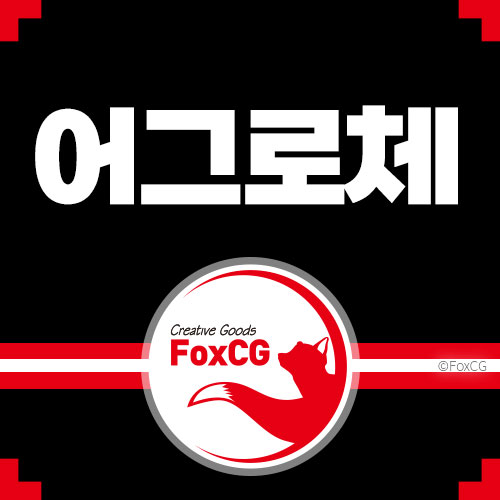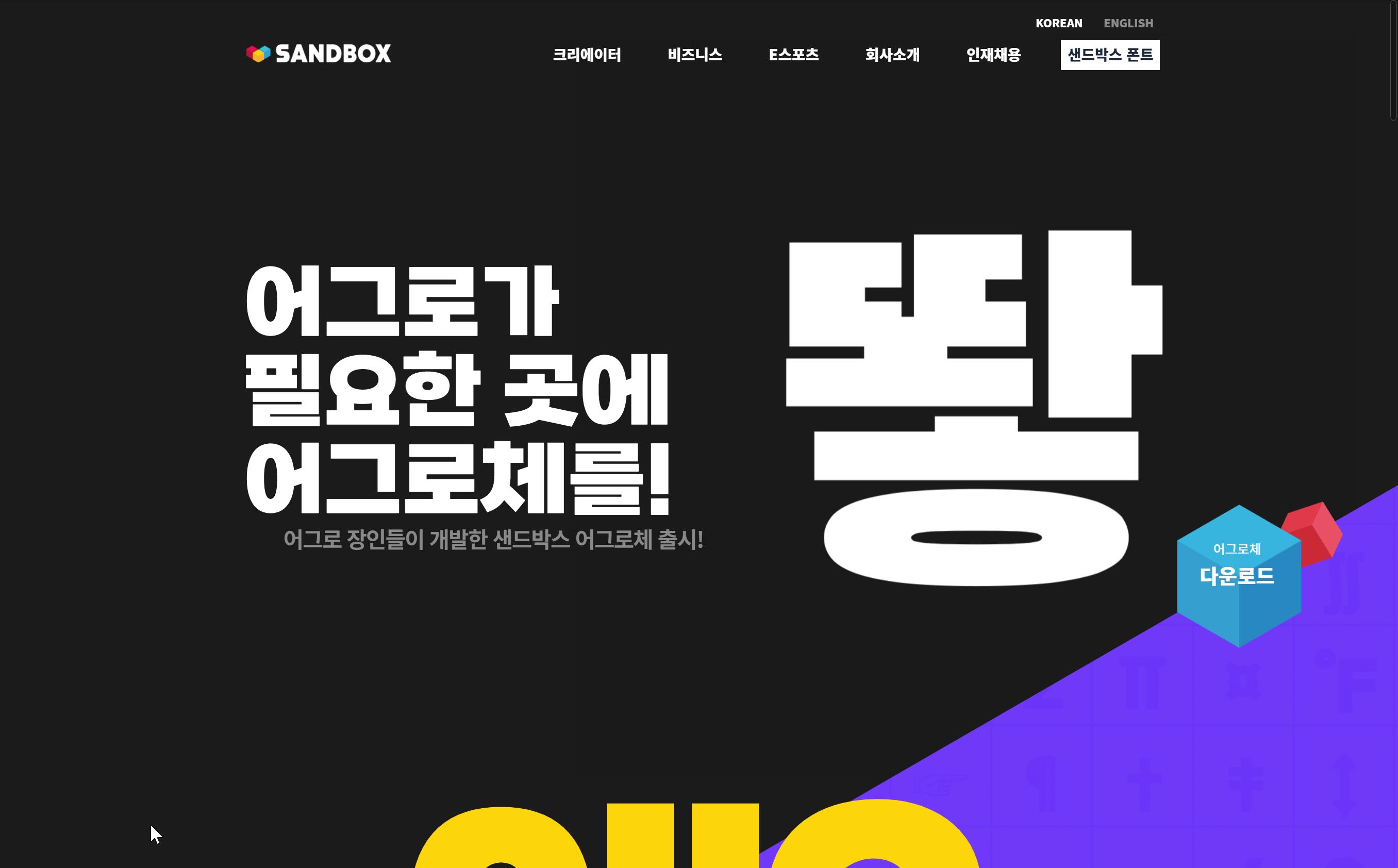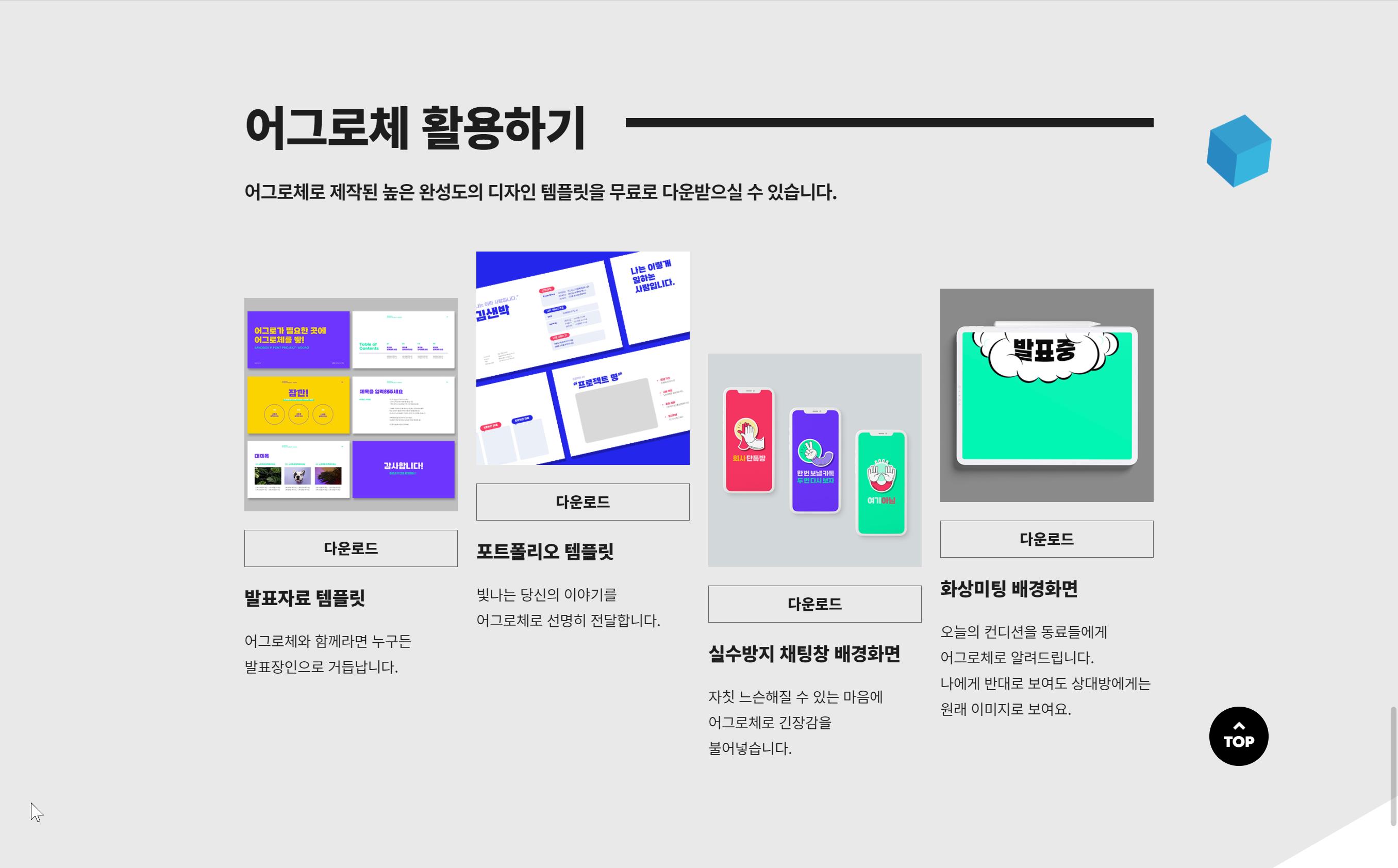
상업용으로 무료로 사용할 수 있는 제목용 폰트 SB 어그로체
유튜브 크리에이터들의 기획사 ‘다중 채널 네트워크’ MCN(Multi Channel Network)중 하나인 샌드박스에서 유튜브 썸네일이나 자막에 사용할 수 있는 전용 폰트인 '어그로체'를 출시했습니다.
샌드박스 어그로체
3가지 두께로 제공되며, 폰트 제작 전문기업인 '디자인210'에서 개발한 폰트입니다.
이스터에그로 '샏'을 입력하면 샌드박스 로고 모양의 하트 아이콘으로 대체가 됩니다.
자주 쓰이는 글자는 아니므로 사용에 불편은 크게 없을 것 같습니다.